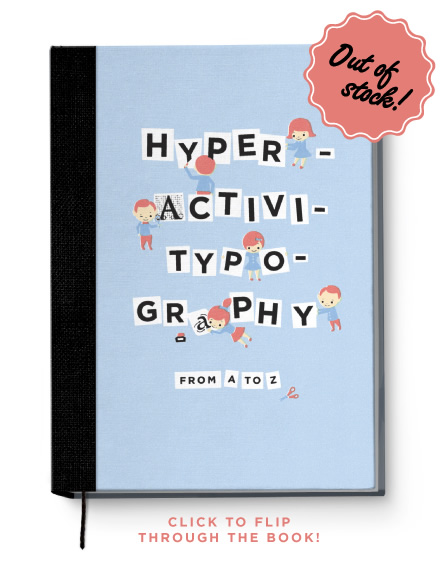
Hace poco todos los lletraferits encontramos este precioso libro y por desgracia para vosotros, los compramos todos. Por lo menos os queda el consuelo de poder disfrutarlo on-line. Son ejercicios básicos sobre tipografía, estructurado como uno de esos libros de ejercicios para escolares de los años 50 y 60, con una estética muy parecida y una impresión acorde a la de laépoca. Os dejo el link a la página del fabricante de papel, Artic, que es el que ha producido el libro por si lo re-imprimen. Os aseguro que es una gozada y mi niño lo está disfrutando (más el padre, evidentemente).